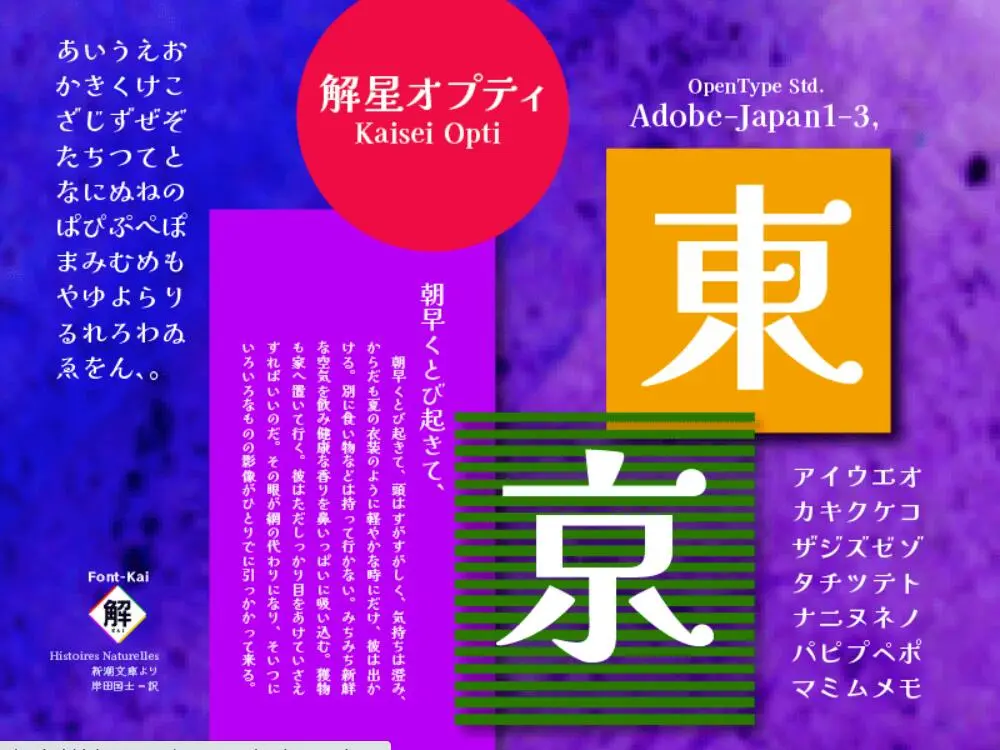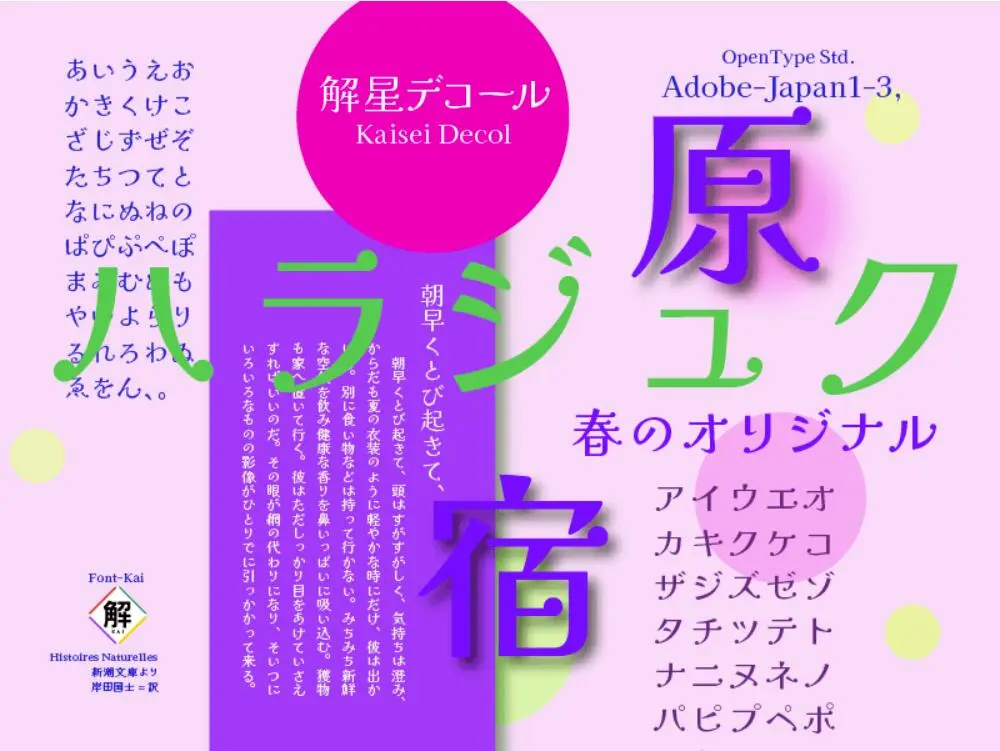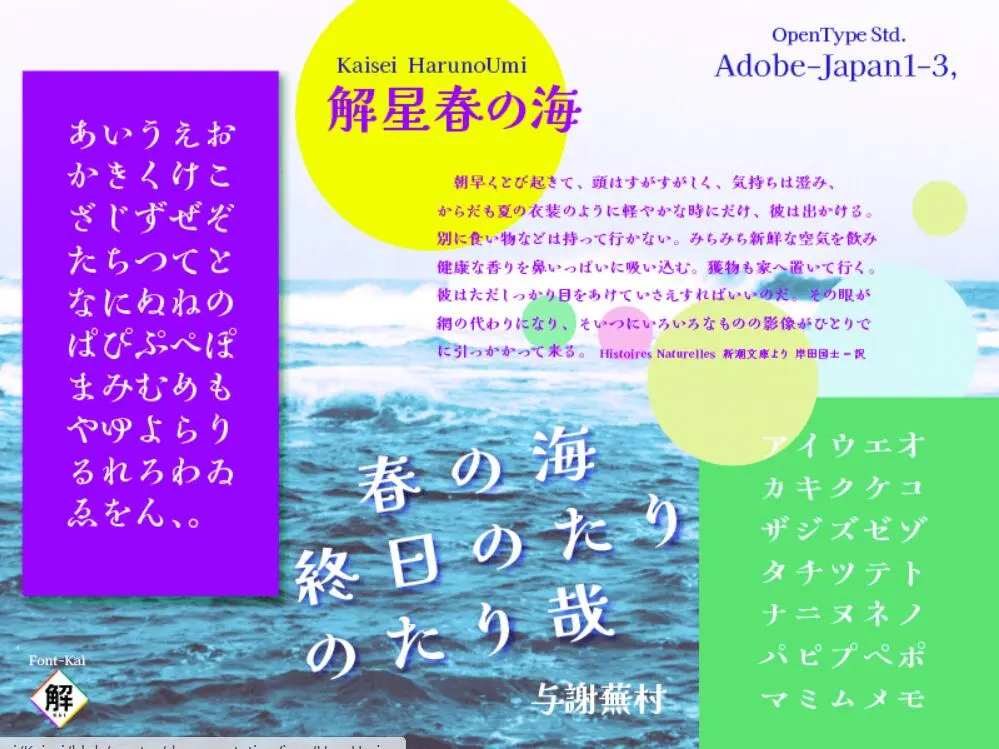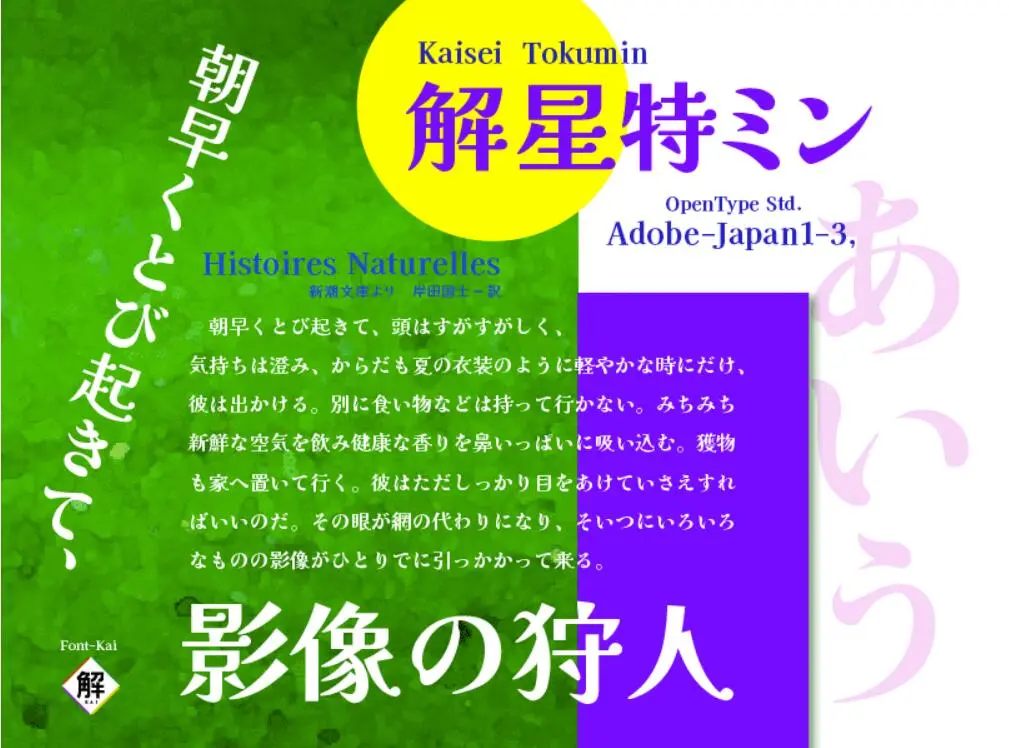
日語字體,一般根據毛筆楷書的書法解釋支撐了根基。日語字體是漢字(1畫~20畫~30畫線・・)和平假名・片假名・歐文・記號類,非常字畫構成有濃度幅度的字形集合。你必須在視覺上調整這些濃度。網絡社會近年來橫排表記變多,另外,也成為與其他語言混植的多重字形集合。我的主題是,尋找一條貫穿日語組版蜘蛛網狀隧道的光明之路。
“解星項目”於2016年開始製作。根據以往的書法的線構成,採用幾何形態的合成來尋找視認性。離開被長期磨礪的毛筆書法會變得不穩定。解星以搔癢的運筆為基礎,與以往的筆法不同,在右付和哈內配置星=點的同時,彌補了離開偕法的不穩定性,導出了新的構成要素。漢字的橫線以前設定為比明朝體粗。這些都是為了提高電子媒體的再現可讀性。
日本語書體は、一般に毛筆楷書に依る書法解釈が根幹を支えてきました。 日本語フォントは、漢字(1畫〜20畫〜30畫線・・)と、ひらがな・カタカナ・歐文・記號類、 大変字畫構成に濃度幅のある字形集合です。これらの濃度を視覚的に整えなければなりません。 Net社會の近年は橫組み表記が多くなり、また、他言語とも混植する多重な字形集合となっています。 私のテーマは、日本語組版の蜘蛛の巣狀のトンネルに(美を以て)貫く光りの道を探すことです。
「解星プロジェクト」は、2016年製作をはじめました。従來書法による線構成から、幾何形態のコンポジションを採り入れ視認性を探した。 永く擦り込まれた毛筆書法を離れると不安定になります。解星では引っ掻くような運筆を基に従來の筆法とは異り、右払いやハネに星=ドットを配置しながら偕法から離れる不安定さを補いつつ、新しい構成要素を導き出しました。漢字の橫線は従來明朝體より太めの設定になっています。これらは電子媒體の再現に可読性を高めるためです。
解星オプティ(Kaisei Opti):是一種現代字體,我認為清新的排版外觀是年輕一代的首選。
解星デコール(Kaisei Decol):假名採用漢字元素=星點的統一設計。因為排版上有很多小點,所以會產生可愛、快樂、和諧的表情。主要用短文的標題發揮效果吧。請好好地分開使用。
解星 春の海(Kaisei HaruUmi):假名融入了搖曳的膨脹,用扭動讓你感覺更接近你的生活。稍小的Katata具有舊明朝體排版的外觀。
解星 特ミン(Kaisei Tokumin):假名是特太明朝體假名的省略。這個字體的目的是標題用強有力的假名。當粗字體的密度增加時,字母底部出現不平衡,單詞失去呼吸。“Kasei Tokumin 是一種厚字體,旨在即使在一群人中也能保持流暢的可讀性,並且不會因強烈的吸引力而失去精緻。